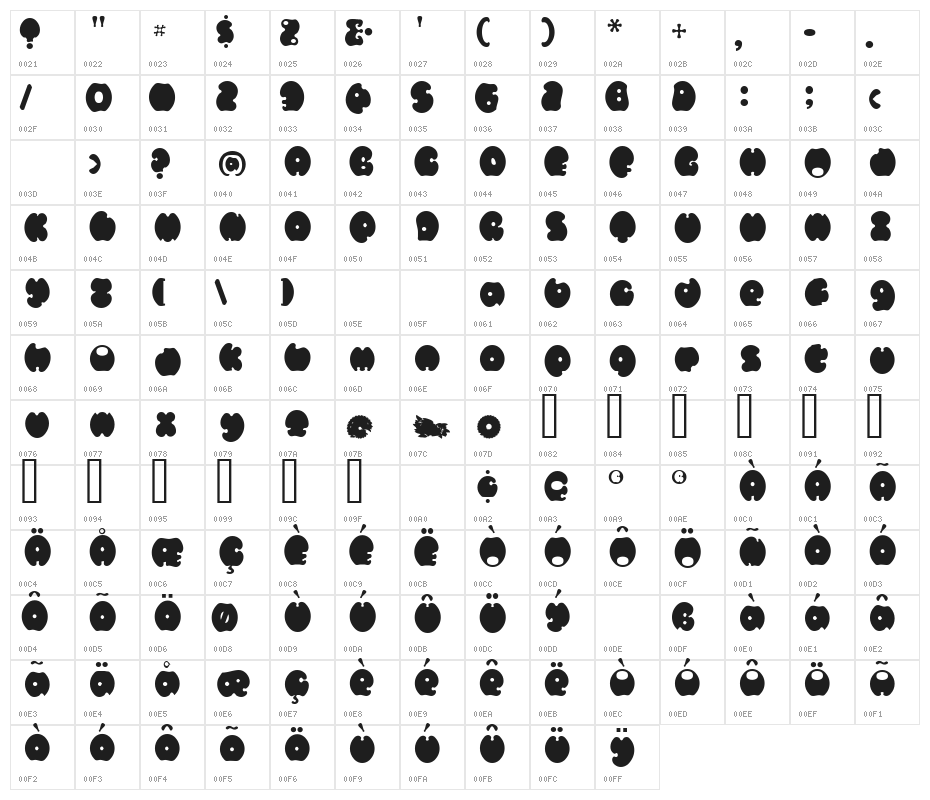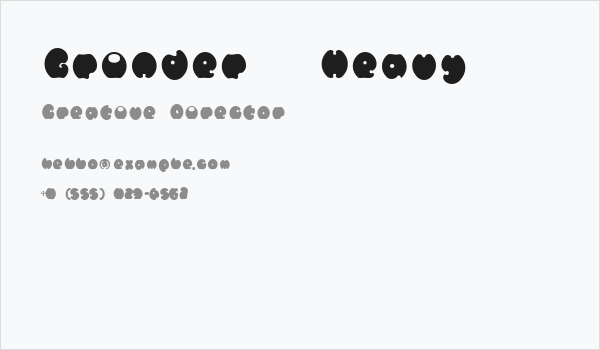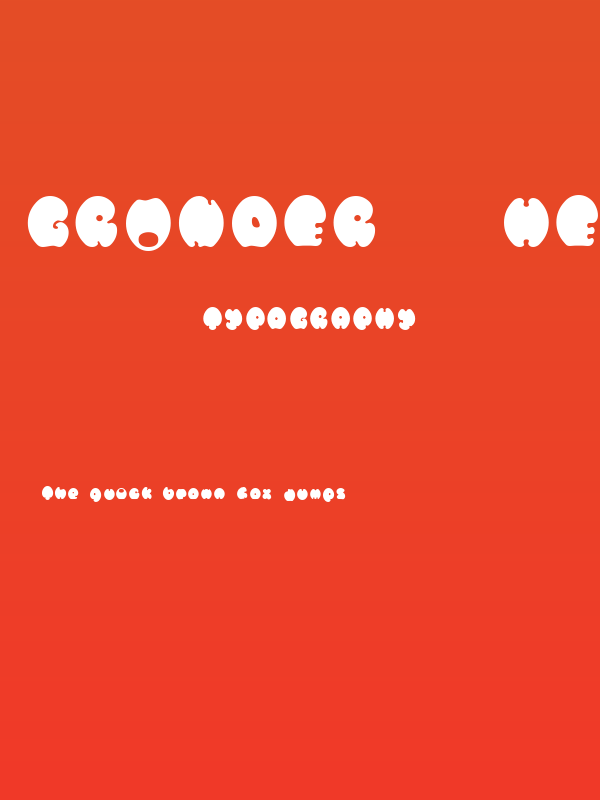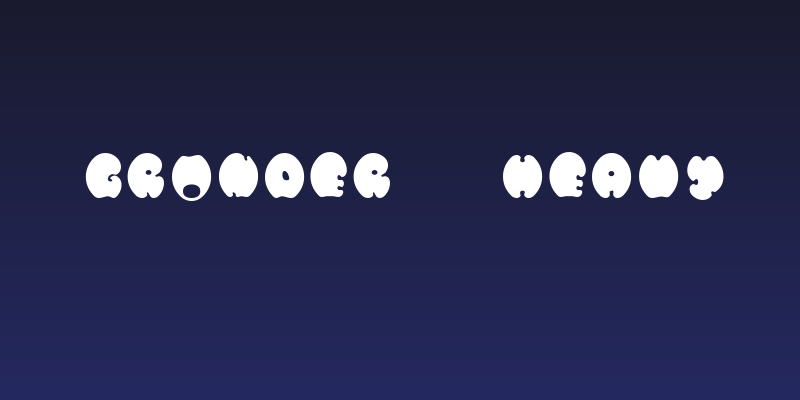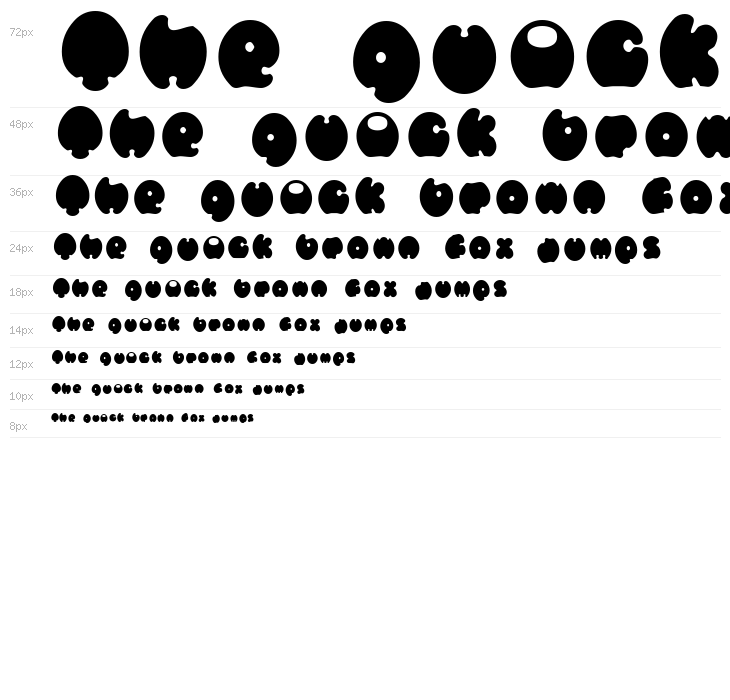
Grinder Heavy Font
| Stile generale | Playful, Whimsical |
| Progetti proposti | Ideal for children's books, comic strips, playful branding, and eye-catching posters. |